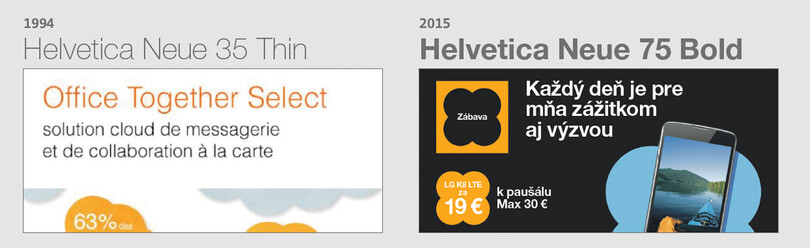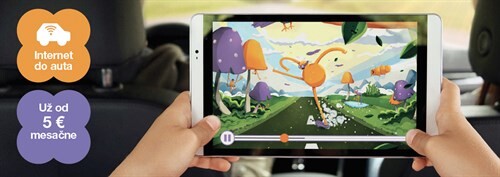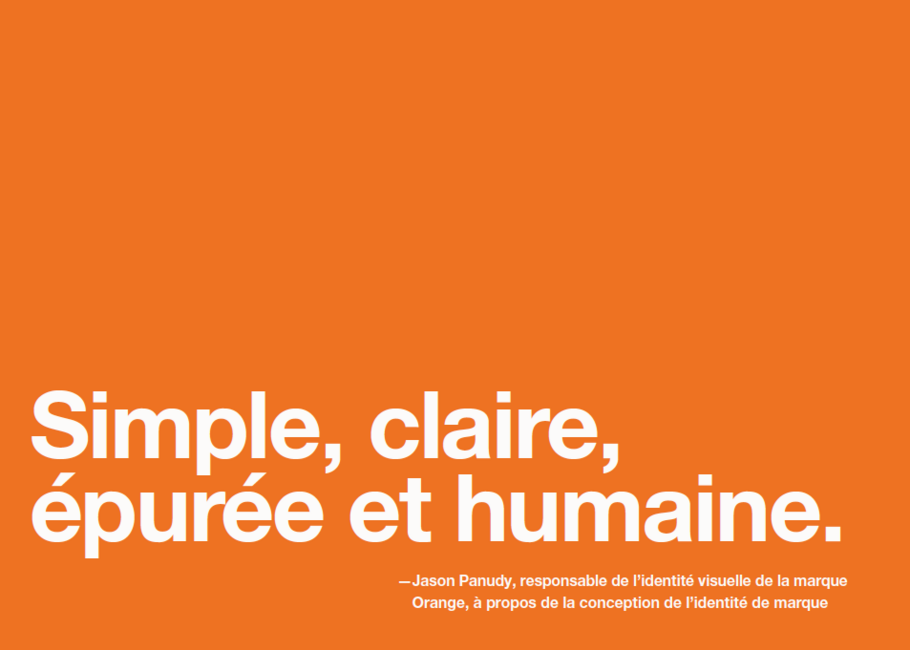
Une plus grande portée numérique et internationale pour Orange.
“ Nos équipes ont besoin d’accéder facilement aux bonnes polices et de savoir qu’elles peuvent les utiliser en toute liberté dans leurs productions. Nous avons désormais la certitude de disposer des licences adéquates et de bien conseiller nos équipes en matière d’utilisation. ”
Jason Panudy, Responsable de l’identité visuelle de la marque
Avec la croissance de ses activités dans de nouvelles régions, Orange a réalisé les limites de ses capacités typographiques. Les nouvelles langues couvertes ont entraîné des incohérences, et les différentes équipes n’utilisaient pas toutes les mêmes licences et les mêmes polices de caractères. Le groupe a commencé à s’inquiéter de problèmes liés à la reconnaissance de sa marque ainsi que du risque de violation de licences.
Monotype a simplifié les licences du groupe en les réunissant en un seul contrat. Cela a permis à Orange de déployer ses polices dans le monde entier dans toutes les langues et dans les environnements numériques émergents sans avoir à s’inquiéter d’un éventuel mauvais usage.
Les origines.
En 1994, le téléphone portable en était encore au stade du gadget coûteux, loin du produit de grande consommation qu’il est aujourd’hui. On le considérait alors comme un objet technologique de pointe adressé à une population limitée de premiers abonnés et d’hommes d’affaires, inaccessible au grand public.
Orange a voulu révolutionner cette situation. « Nos concurrents s’obstinaient à parler technologie, ce qui déroutait et intimidait le grand public », explique Jason Panudy, responsable de l’identité visuelle de la marque Orange. « Dès sa création, Orange a été la marque qui rendrait cette technologie plus humaine. Nous parlions des avantages de la communication personnelle, et non des appareils. Toute notre identité s’est construite autour de cette idée : simple, claire, épurée et humaine. »
“ Orange a été la marque qui rendrait cette technologie plus humaine. Nous parlions des avantages de la communication personnelle, et non des appareils. Toute notre identité s’est construite autour de cette idée : simple, claire, épurée et humaine. ”
Une identité de marque centrée sur la simplicité et la clarté demandait une police de caractère tout aussi directe et accessible. D’une grande lisibilité, avec son tracé classique et épuré, Helvetica Neue « en était la parfaite représentation », ajoute Jason Panudy. Choisie en 1994, la police est devenue synonyme de la marque au cours des décennies qui ont suivi.
Les défis d’une marque en pleine croissance.
Dans le cadre d’un projet d’évolution globale de la marque déployé en 2015, Orange a caressé l’idée de changer de police de caractères. « Finalement, c’est d’Helvetica Neue qu’est venu le changement dont nous avions besoin, sans le coût et les bouleversements liés à un changement complet », se souvient Jason Panudy.
« Passer d’une police principale en 35 Thin à 75 Bold nous a permis d’obtenir une typographie plus solide et conforme à notre orientation de marque sur des canaux numériques bien plus importants que nous aurions pu l’imaginer en 1994. »
Cependant, avec une empreinte géographique et numérique grandissante, le groupe peinait à rester cohérent avec la licence existante sur tous ses marchés et ses canaux, en particulier sur ses sites internet et ses applications. « Avant de travailler avec Monotype, nous collaborions avec un prestataire, et certaines filiales nationales géraient elles-mêmes leurs propres licences. »
Les ambitions internationales du groupe ont également été sources de problèmes. « Les langues représentent un véritable défi quand on arrive sur un nouveau territoire », explique Jason Panudy. « Par exemple, notre équipe jordanienne a utilisé Helvetica World pour ses messages en arabe alors que nous utilisions 35 Thin comme police principale. Comme Helvetica World ne gérait pas ce style, nous nous retrouvions avec des incohérences typographiques. »
Orange a réalisé qu’il était temps de revoir sa stratégie de licence de police. Au lieu d’une approche morcelée, le groupe avait besoin d’une licence prête à l’emploi, simple, et adaptable à la croissance de la marque pour éviter d’éventuelles nuisances à son intégrité visuelle et tout risque de violation de licences. Il avait besoin d’une entreprise pouvant le conseiller et lui fournir une assistance créative, juridique et technique.
C’est à ce moment-là que Monotype est entré en scène.
La simplicité comme solution évidente.
En travaillant avec Monotype, Orange a pu développer une licence d’entreprise éliminant les coûts et les difficultés liés à l’achat de licences individuelles pour chaque cas, chaque pays ou chaque langue.
« Nous avons discuté avec Monotype au sujet des différentes options possibles concernant notre projet d’évolution de la marque », raconte Jason Panudy. « Nous voulions nous assurer que nos licences résisteraient à l’épreuve du temps et, plus particulièrement, pouvoir les mettre à jour pour nos plateformes en ligne. Nous avons simplement fait part à Monotype de nos besoins, et ils sont revenus vers nous avec la solution adéquate que nous avons ensuite ajustée à chaque cas. »
Et surtout, Orange peut continuer à développer sa marque avec l’assurance que son identité visuelle est protégée et prête pour les années à venir.